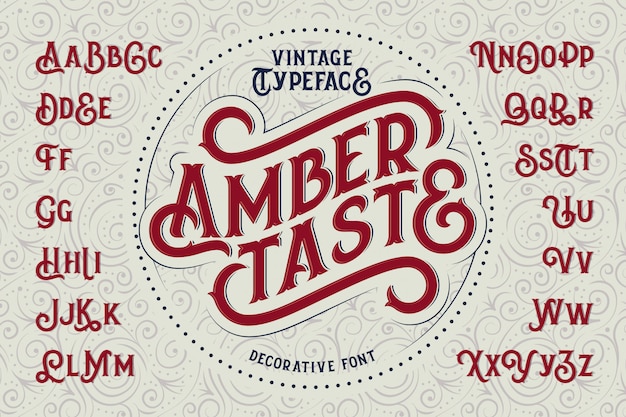
Декоративный шрифт или дисплей, шрифты обладают индивидуальностью. Эти шрифты представляют собой богато украшенные версии шрифтов без засечек, с засечками, скриптов и других стилей шрифтов. Смысл использования декоративного шрифта в том, чтобы привлечь внимание действительно уникальным внешним видом. Как следует из их названия, декоративные шрифты следует использовать в декоративных или декоративных целях. Они не подходят для использования в основном тексте.
Bagawantha Font
Bagawantha Font — декоративный шрифт, воплощающий этническую атмосферу, уникальность и сильный характер. Этот шрифт тщательно разработан, чтобы передать богатство культурного наследия и незабываемую красоту.
Master Lemon Font
Master Lemon Font — это симпатичный и яркий рукописный шрифт, готовый сделать ваши проекты великолепными и забавными! Используйте его с уверенностью в своих проектах, таких как цитаты, поздравительные открытки, приглашения, плакаты, визитные карточки, презентации и многое другое!
Шрифт Manda
Шрифт Manda — вдохновлен одним из мотивов Manik Dayak, который является коренной культурой даяков, Калимантан, Индонезия.
Шрифт Speed Boom
Шрифт Speed Boom — это быстрый игровой шрифт без дисплея, который сделает ваш дизайн запоминающимся! Шрифт хорошо работает со многими проектами, такими как логотип бренда, игровые меню, обложка, этикетки, плакаты, названия фильмов, вывески, веб-сайты и многое другое!
Шрифт Gaman Guneman
gaman guneman , индонезийский традиционный шрифт
Modern Neon Font
Modern Neon Font — ослепительный дисплейный шрифт, излучающий неоновый свет и футуристическая атмосфера. Этот шрифт с заглавными буквами привлекает внимание, создавая визуально ошеломляющий опыт, который оставляет неизгладимое впечатление.
Шрифт Neon Street
Neon Street Font — это декоративный неоновый шрифт, вдохновленный ночными неоновыми световыми вывесками в стиле ретро. С его жирными заглавными буквами и встроенными элементами в неоновом стиле этот шрифт излучает энергию и создает визуально ошеломляющий опыт.
Шрифт Neon Vibes
Шрифт Neon Vibes — это забавный и игривый ретро-шрифт с неоновым светом, который привносит нотки 80-х в ваши проекты.
Этот шрифт с крупными жирными заглавными буквами и завораживающим неоновым стилем передает суть живой и динамичной атмосферы..
Neonrec Font
Neonrec Font — современная и стильная группа жирных шрифтов без засечек, состоящая из заглавных букв. Этот шрифт с яркими заглавными буквами и яркой неоновой подсветкой привлекает внимание, создавая визуально ошеломляющий и дальновидный опыт.
Kerambit Font
Этот шрифт вдохновлен индонезийским традиционным оружием из Минангкабау, которым является Kerambit
Megamendung Font
megamendung — единственный в своем роде батик из Индонезии
Zeneon Font
Moggly Font
Moggly Font — забавный и причудливый дисплейный шрифт. Он станет хитом для каждого из ваших детских или школьных проектов! Добавьте этот красивый дисплейный шрифт к каждой из своих творческих идей и обратите внимание, как он выделяет их!
Oakland Font
Oakland Font — это дисплейный шрифт с современным оформлением. Он будет идеально использоваться для брендинга, дизайна логотипов, надписей, логотипов, одежды, плакатов, журналов, упаковки, плакатов, сумок для покупок, футболок, обложек книг, фотографий, специальных мероприятий и других дизайнерских проектов.
Bahrwang Font
Bahrwang Font — шрифт, вдохновленный и посвященный одному из самых известных балийских традиционных танцев, Barong Bali
Sketch Written Font
Эскиз Письменный шрифт — это шрифт, который изображает повторяющиеся рукописные каракули. Этот шрифт, созданный для придания эксцентричного и креативного вида написанному от руки, создает уникальную и личную атмосферу в дизайне.
Noe land Шрифт
Noe land Font — это шрифт, воплощающий тему свободы. Разработанный со смелостью и исследованием, он олицетворяет дух независимости и безграничного творчества. Благодаря своим уникальным и выразительным характеристикам Noe Land обеспечивает смелый и увлекательный вид для различных дизайнерских проектов.
Wylon Outline Font
Wylon Outline Font — это шрифт, изображающий жизнерадостность и счастье, вдохновленный миловидностью животного. В процессе его создания мы черпали вдохновение в игривости и жизнерадостности, излучаемых поведением и характеристиками животных.
Шрифт Iron Lien
Шрифт Iron Lien — это современный шрифт, воплощающий силу и динамизм в каждой букве. Разработанный в ярком и современном стиле, этот шрифт подходит для различных дизайнерских проектов, требующих мощного и смелого впечатления.
Шрифт Boxkan
Шрифт Boxkan — это современный дисплейный шрифт, который придает мощь и смелость каждой из его букв. Разработанный в ярком и современном стиле, этот шрифт подходит для различных дизайнерских проектов, требующих сильного и смелого впечатления.